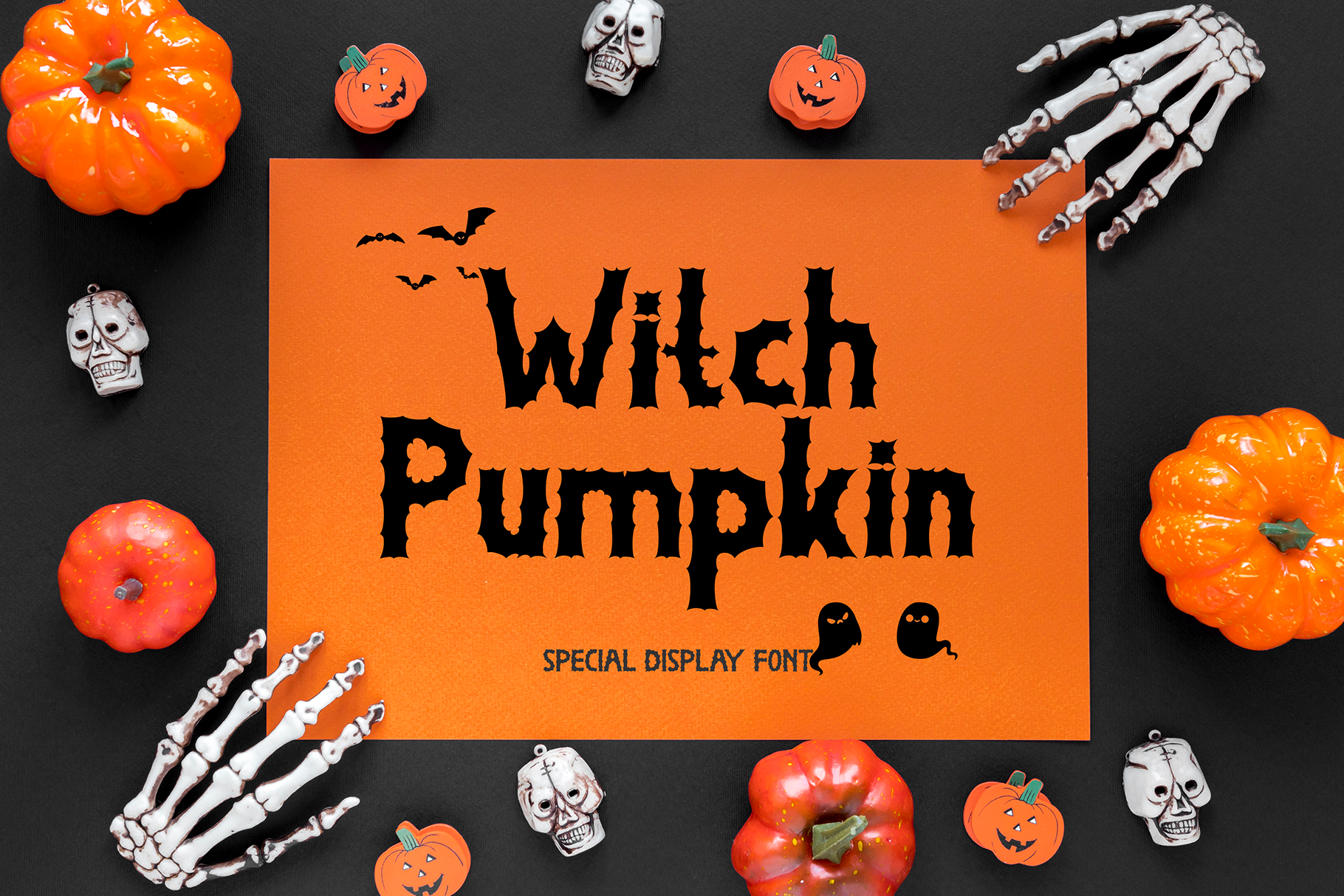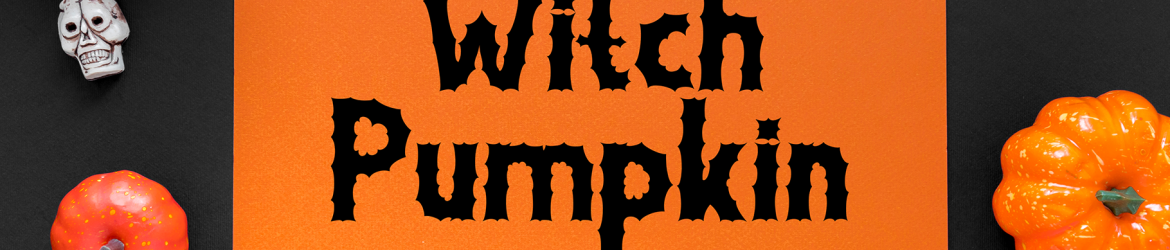
Esta é uma fonte tipo display chamada ‘Witch Pumpkin Font’, criada pelo designer Yoga Letter. Ela traz uma sensação cool e aventureira que é perfeita para aqueles momentos festivos onde você quer destacar seu design com um toque único e assustador. Suas formas espalhadas e letras fortes não apenas suportam designs variados, mas também se destacam especialmente em trabalhos relacionados ao Halloween ou a festas de outubro. Atrai os olhares com sua atmosfera sinistra e criativa, tornando-a uma opção versátil para qualquer projeto que deseje dar um toque especial de fantasia e espirito escuro. Seja você designer gráfico, ilustrador ou editor digital, este é o tipo de fonte que irá fazer sua arte se destacar ainda mais neste período do ano.